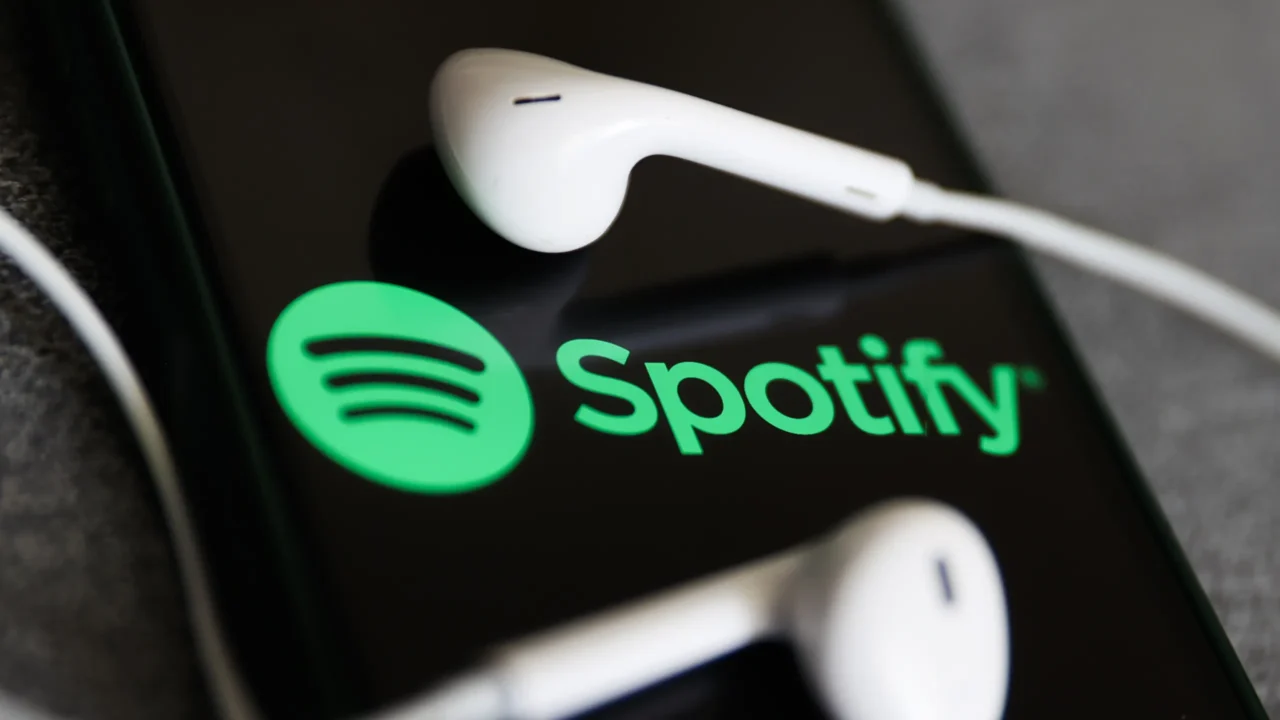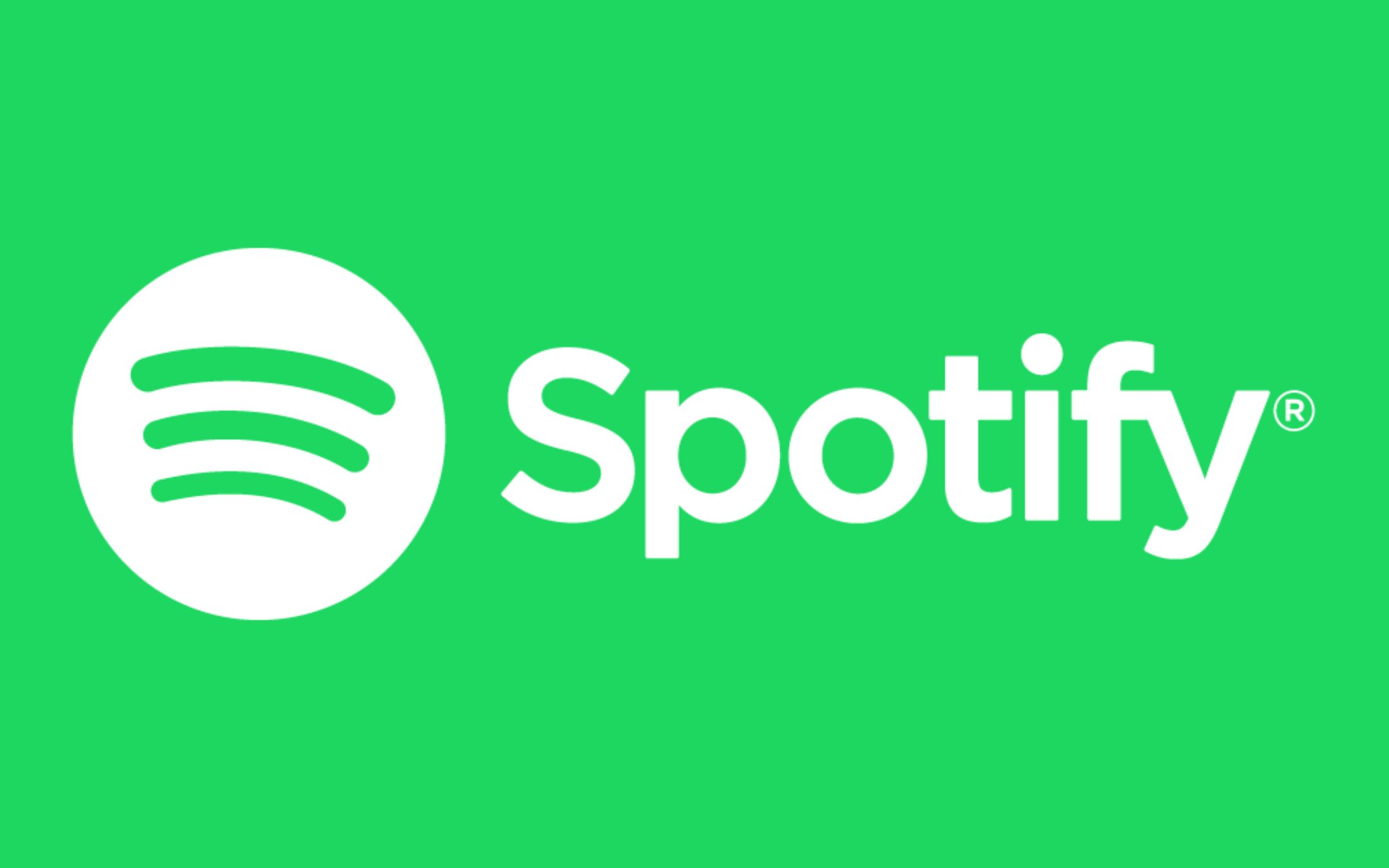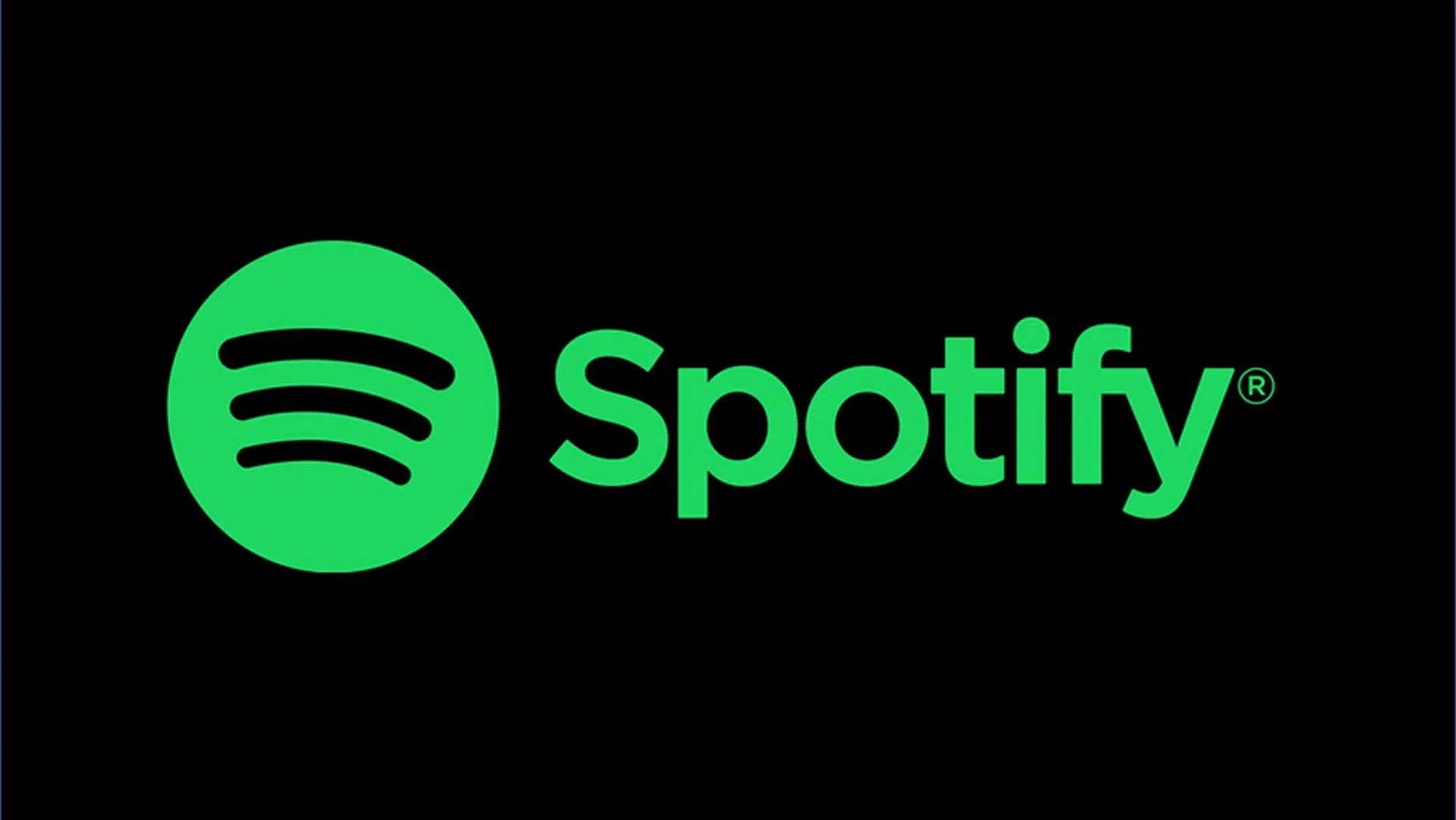
La piattaforma per lo streaming musicale lancia un nuovo font che prende il nome di Spotify Mix, disegnato da Dinamo Typefaces, e che verrà utilizzato per tutte le sue interfacce. Scopriamolo insieme.
Font Custom: perché è importante
Ormai moltissime aziende scelgono di distinguersi dalle altre realizzando dei font personalizzati. È essenziale oggigiorno, in un mondo dove trovare font a basso costo è molto semplice e si rischia di perdere quel senso distintivo che rende i diversi brand riconoscibili.
Anche Spotify come molte altre aziende, quindi, sceglie la strada del font custom. In questo caso la piattaforma ha affidato la realizzazione del proprio font a Dinamo Typefaces, famoso proprio per i suoi lavori di type design.
Il font custom influisce notevolmente anche sulla brand image, diventando uno degli elementi fondamentali della stessa. Avere un nuovo font, infatti, vuol dire anche modificare il proprio logotipo.
In alcuni settori, inoltre, è fondamentale trovare il modo di distinguersi. Proprio in un settore come quello dello streaming musicale, dove per accedere alle diverse funzioni bisogno passare da un’interfaccia visiva, avere una brand image efficace è molto importante.
Spotify: il vecchio font
Il vecchio font della piattaforma si chiamava Circular ed è stato utilizzato per tutte le funzioni fino a non molto tempo fa.
Il limite principale di questo font era, tuttavia, il numero di stili, i quali sono solamente 16. Potrebbe sembrare un numero sufficiente, ma per una piattaforma come Spotify in realtà non lo è.
Come molte piattaforma, infatti, essa deve adattarsi a tante diverse schermate, dispositivi e canali di comunicazioni, e 16 diventa un numero troppo limitato per riuscire a fare ciò.
Inoltre, i font non servono solo a scrivere nero su bianco delle informazioni, ma devono anche trasmettere delle sensazioni e delle emozioni. Ad esempio, dovremmo essere in grado di capire il tipo di contenuto audio o il genere musicale anche semplicemente dalle percezioni che lo stile del font ci trasmette.
Grazie a Spotify Mix la piattaforma è riuscita a ottenere questo risultato. Esso, infatti, ha un gran numero di stili.
Spotify Mix: il nuovo font della piattaforma
Spotify “è fatto per muoversi ad ogni volume”, così lo descrive l’azienda stessa al suo debutto.
Il font, progettato, come abbiamo detto, da Dinamo Typefaces, ha richiesto un lungo lavoro durato un anno e mezzo.
Anche un esperto del settore come Dinamo Typefaces ha impiegato un lungo periodo di tempo per progettare questo font, perché la sfida richiesta dall’azienda era notevole.
Il font, infatti, deve essere leggibile e funzionare su tutti i dispositivi e le interfacce. Allo stesso tempo, però, deve avere un carattere marcato e un’alta dinamicità, in modo da adattarsi a tutti i diversi stili e generi proposti da Spotify.
Spotify Mix è un font senza famiglia
Per riuscire a vincere questa sfida i designer sono dovuti uscire dagli schemi tradizionali e progettare un font senza famiglia.
Solitamente, infatti, anche quando un font è custom made rientra in una famiglia, perché con essa condivide una serie di caratteristiche.
Spotify Mix non condivide caratteristiche con una sola famiglia, ma con molte di esse e per questa ragione non può essere catalogato sotto nessuna di esse.
Di base questo font è un sans serif, ma ha diversi elementi che non rientrano in questa categoria. Ad esempio, la S, sia quella in maiuscolo che quella in minuscolo, si ispira ai font veneziani, mentre la J e la K si traggono ispirazione dai font grotteschi.
Con l’arrivo di un nuovo font personalizzato, ovviamente, è arrivata anche la decisione di modificare il logotipo del brand.
Di conseguenza possiamo vedere un restyling quasi completo della brand image dell’azienda.